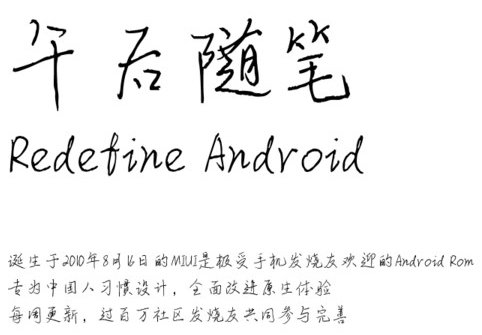
午后隨筆字體是漢儀字庫推出的一款閑雅慵懶的手寫字體,讓大家感受午后的的寧靜和放松,讓你的文字更有味道,綠色資源網(wǎng)誠意推薦!
一杯咖啡、一頁紙、一支筆、一縷陽光,一個屬于自己的午后時光……
午后隨筆體字跡清晰而沉穩(wěn),如時光般的透徹與可貴,給人一份慵懶而認(rèn)真的生活態(tài)度體驗(yàn),讓文字擁有自己的靈魂,可以適用在藝術(shù)設(shè)計、文化排版、包裝策劃等場合當(dāng)中。